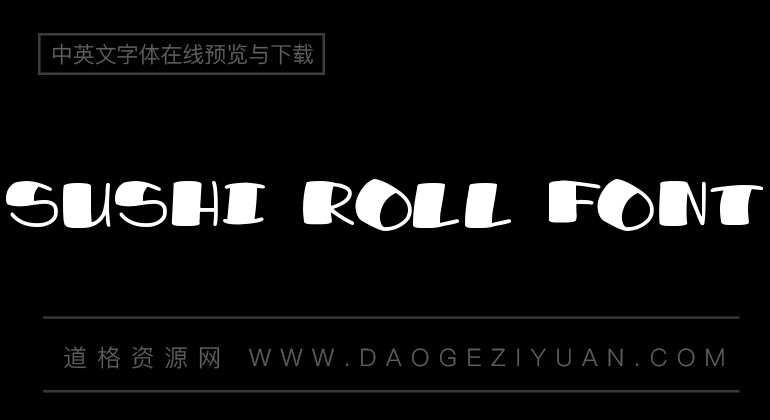
Sushi Roll Font 是一种漂亮的手写风格字体,其设计灵感来自于日本传统的寿司文化。这种字体的线条流畅,有很强的艺术感和设计感,非常适合用于海报、广告、产品包装、印刷品等方面的设计。 这种字体的特点是非常清晰可读,同时也非常美观。它的每一个字母都经过精心设计和优化,使得整个字体看起来非常协调和和谐。此外,该字体支持英文字母和数字,可以满足各种设计需求。 Sushi Roll Font 还可以在许多不同的环境中使用,比如在网页设计、应用程序界面、电子邮件设计等方面。总之,如果你需要一种漂亮、清晰可读的手写风格字体来增强你的设计效果,Sushi Roll Font 无疑是一个不错的选择。内容介绍
Sushi Roll Font是一款非常不错的手写艺术字体,具有很好的视觉感,适合于文化类的宣传设计、商业类品牌的广告和产品包装设计以及个性化文字排版等较多场景。